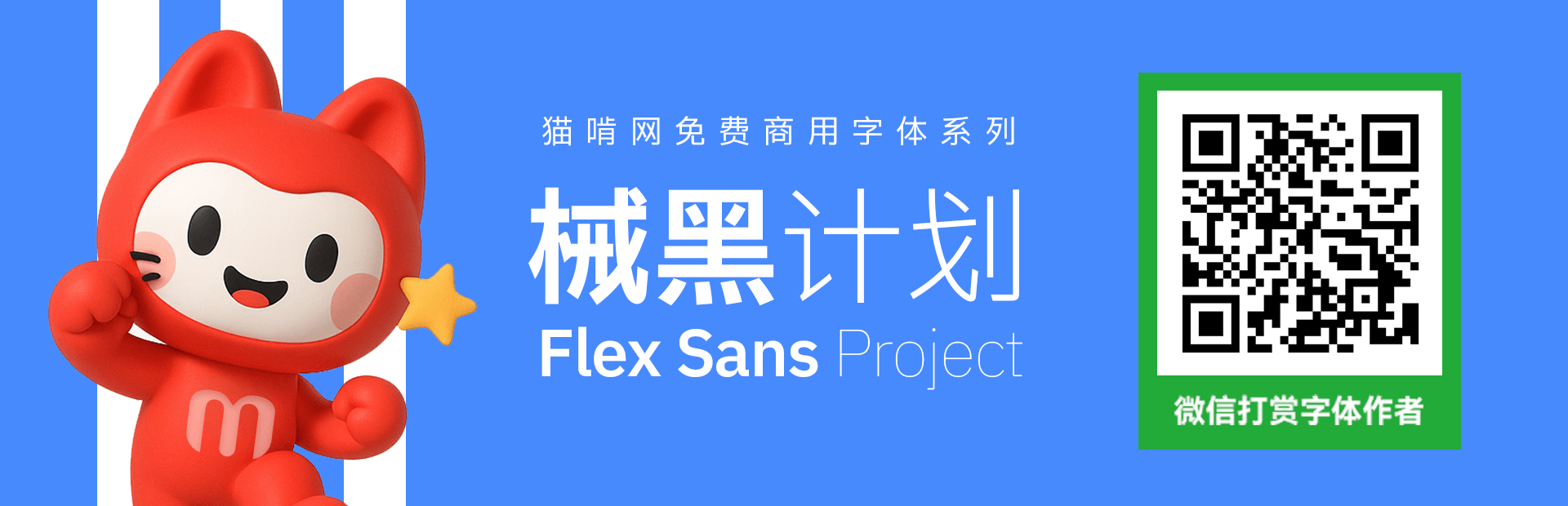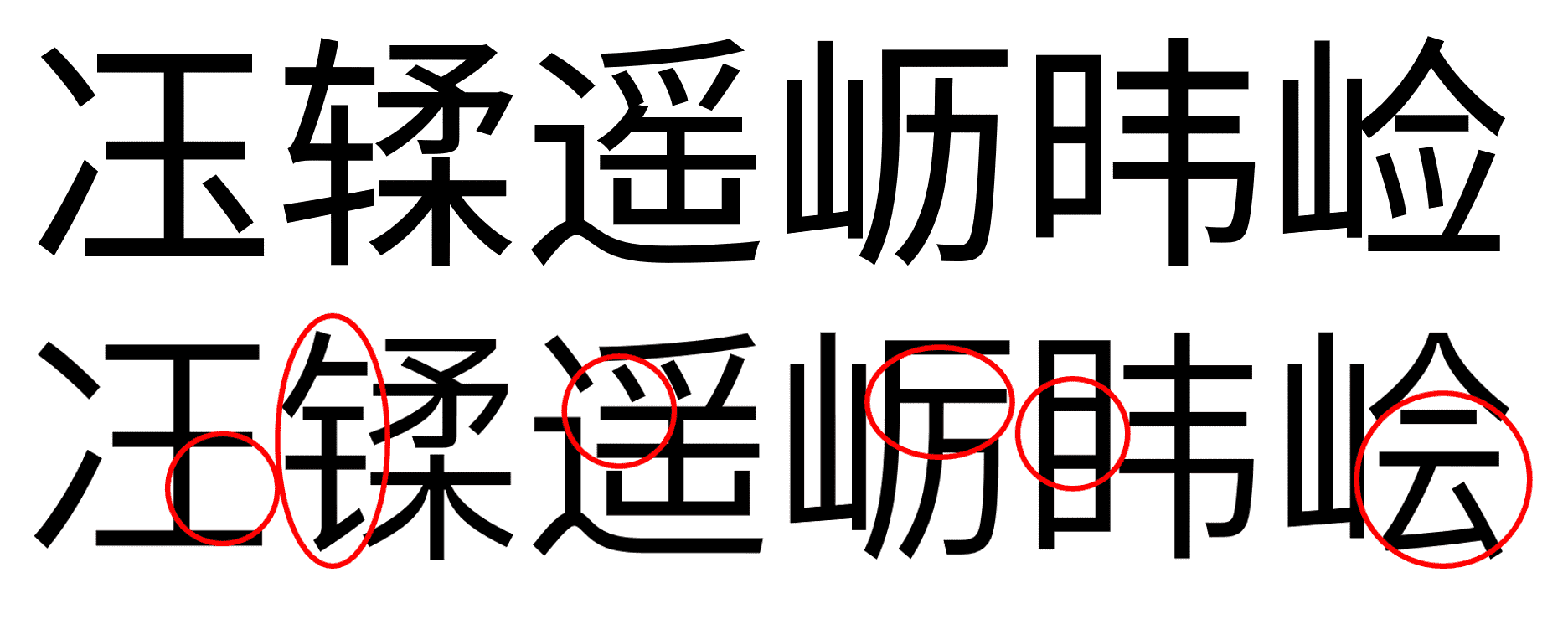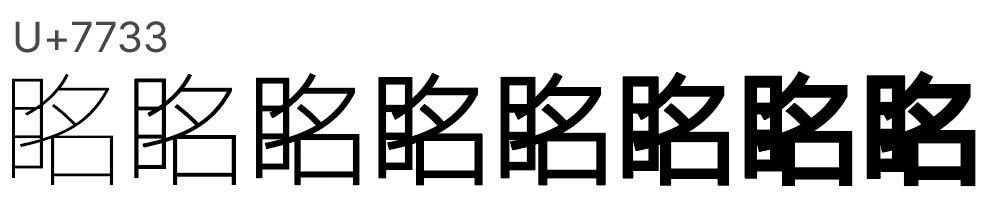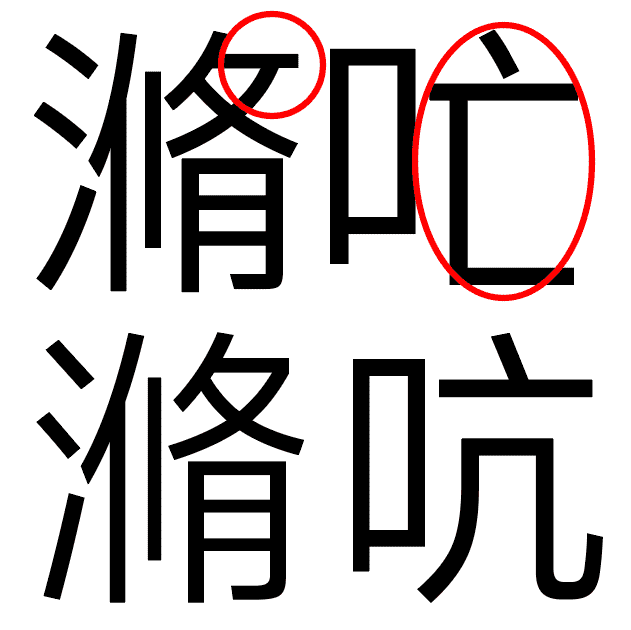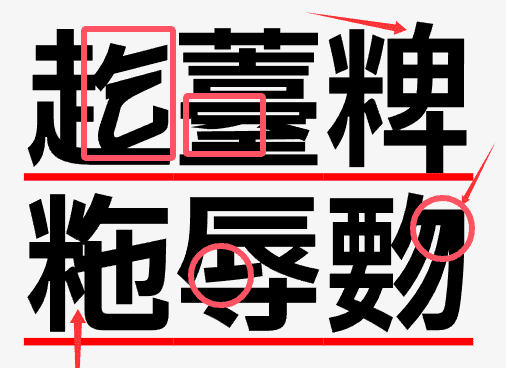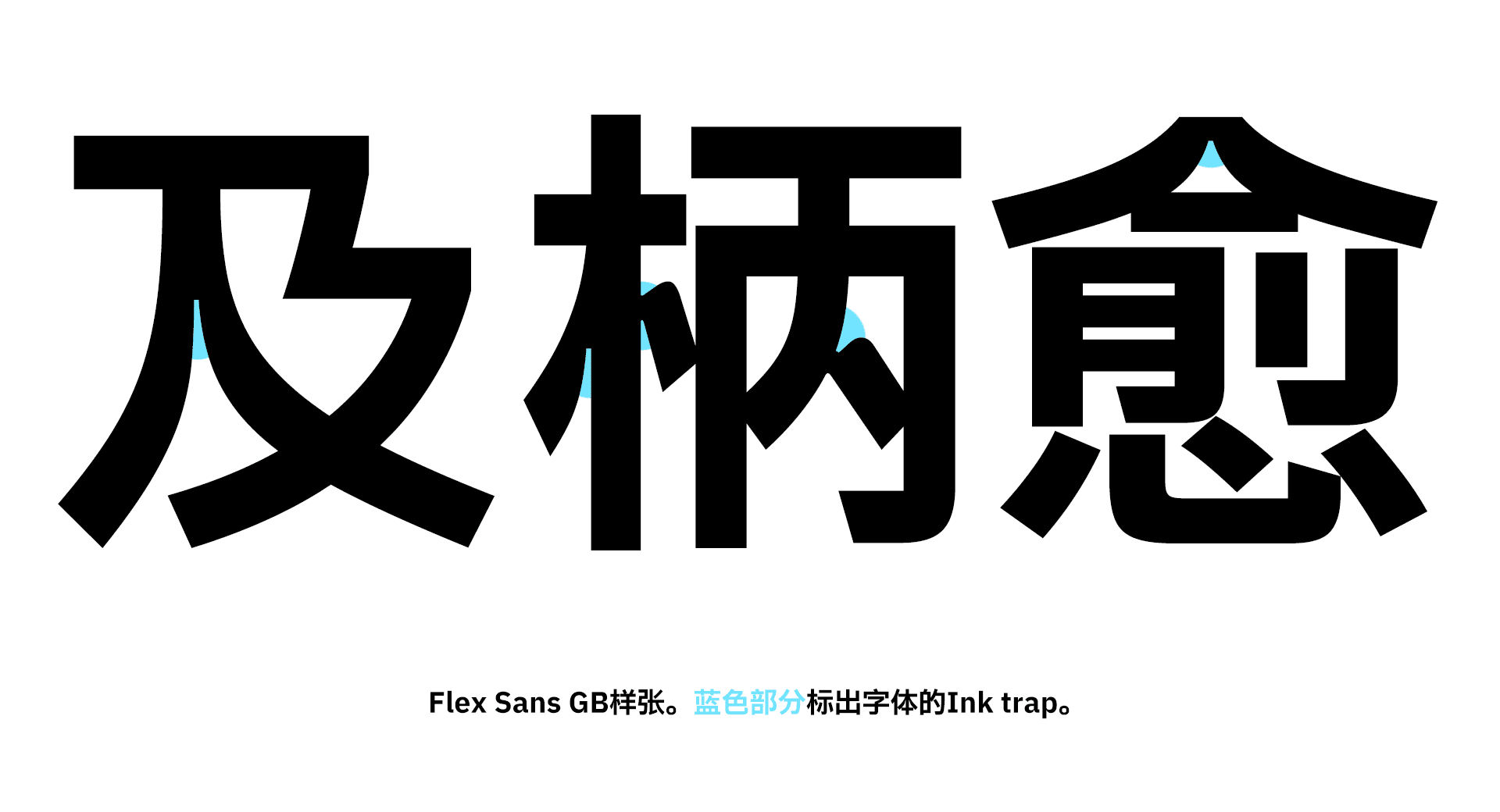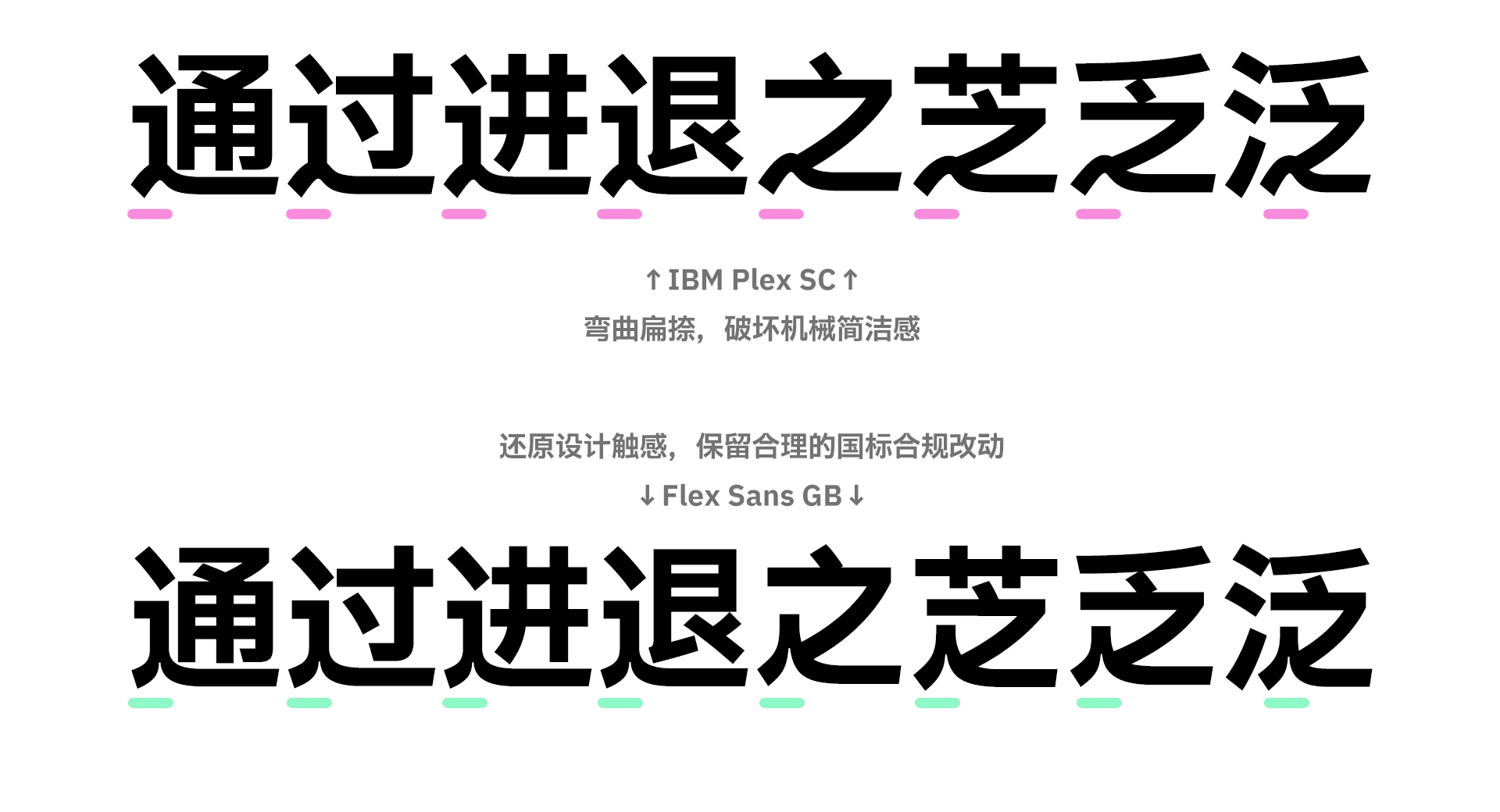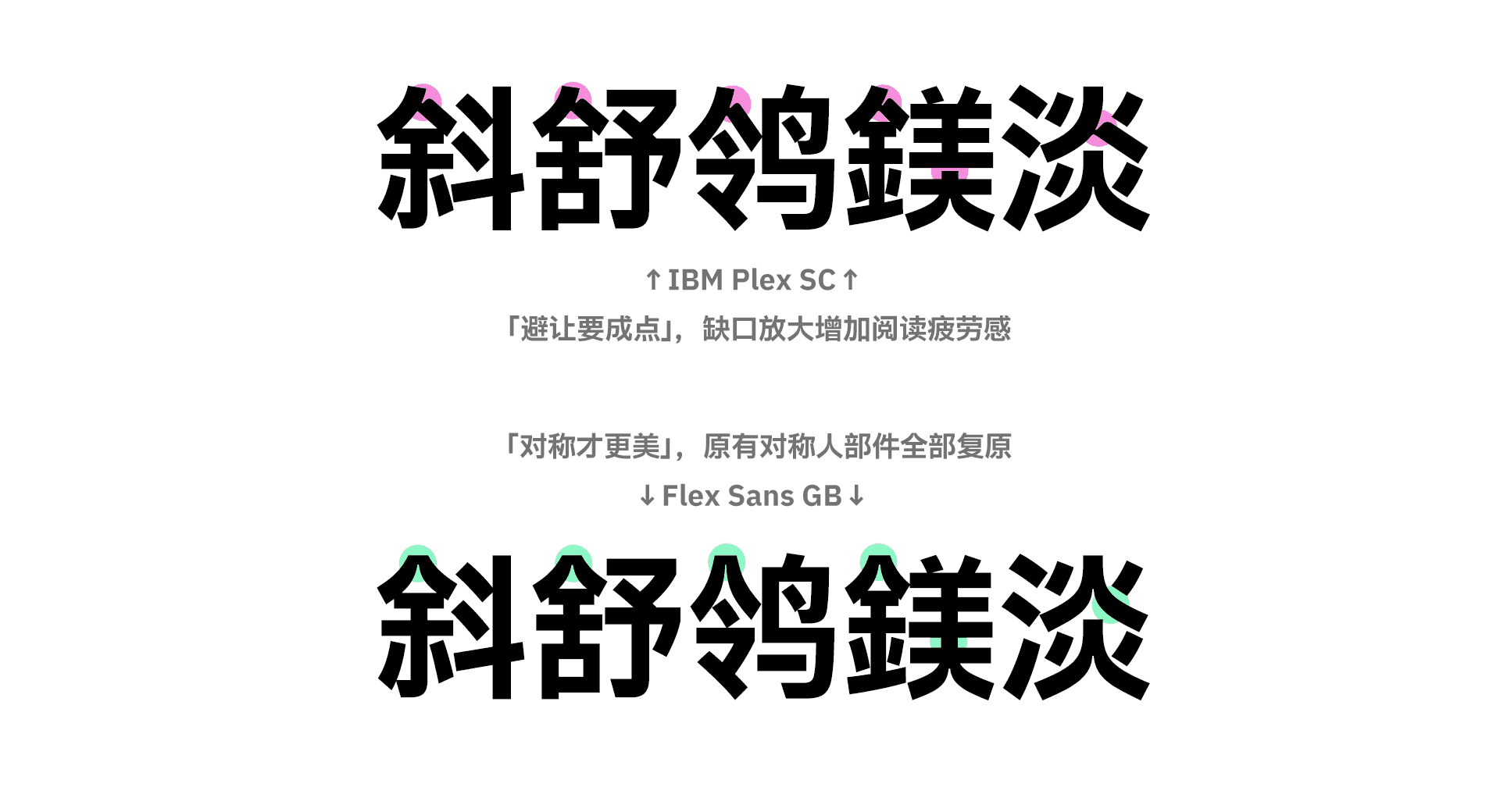
项目起因
IBM Plex,和一再放鸽子的IBM Plex CJK
IBM Plex是IBM公司于2017年发布的开源字体项目,在当时便预告说「会制作相应的CJK(中日韩)字体,预期在2018年中发布」,吊足胃口。可延期又延期,直到2021年7月,日文版才总算发布。其中汉字部分的设计上延续西文部分独特的ink trap表现,轮廓融合机械与人文,不失简约感,令人十分期待扩充汉字字数后的繁体和简体版。在用户的期待、敦促和不安中,2024年8月末我们迎来了其繁体版的发布,也可圈可点。一切似乎很顺利。
谁能想到IBM Plex Sans SC这么糟
可好景不长,后续发布的IBM Plex黑体简体版(下文称IBM Plex Sans SC,SC即「简体版」)令人大跌眼镜,不仅出于所谓「符合国标规范」的理由,将大量合理设计全部推翻,改为突兀而不合群的设计,令人费解,甚至出现了大量明显错字、轮廓错误变形等,尽显赶工丑态。大量遗漏未修改的断笔竖点更是自打「符合国标」的嘴巴。
Plex SC 部件比例错误
Plex SC 更多错字错形
Plex SC更多形体问题
Flex Sans GB的形成
直到2025年4月,IBM才匆匆发布Plex的字体源代码,我们也总算有机会对IBM Plex Sans SC的诸多问题拨乱反正,并得以借此制作汉字部分的可变字体版本。
项目创立时,我们先从中拿出简体中文实际会使用到的文字进行修改,并逐步确立了「尊重日文版和繁体版的原有设计风格,复原简体版不必要的修改」这一目标。历经几个月的修改工作,我们已初步将IBM Plex Sans SC中成部件的大量不必要修改还原成字体的原有风格,并修复了其中的一部分错形,部分零碎的字形也已恢复到繁体版和日文版原本的设计。时机成熟,我们决定发布成果,将这一恢复原本设计但也符合国标、拥有可变版本的字体命名为「Flex Sans GB」。
项目概览
人文机械巧结合
「按下键帽,金属臂带动字模,凸出的字形透过墨水晕印纸上。」这便是这套字体的灵感来源,IBM最初的产品之一,IBM Selectric打字机的感觉。Flex Sans GB继承IBM Plex CJK原版风格,从打字机中汲取灵感,在具有早期铅字的ink trap墨陷设计的同时,轮廓则尽可能简洁而倾向几何化,呈现出金属一般的利落感,兼具人文和机械特征,总体上在维持字体情绪为中性的同时,引入了与其他黑体与众不同的设计风格。
接下来,我们会介绍Flex Sans GB相对于IBM Plex Sans SC的改动,解释后者存在的问题,以及Flex Sans GB如何复原原始设计解决这些问题。
扁捺何须弯弯绕
对比扁捺,还原不必要修改(需更新)
IBM Plex Sans SC最为人诟病的修改,其中一个便是将大量的扁捺笔画改动成带有手写笔画特征的弯曲扁捺设计,破坏了原本设计简洁不失人文的特征,集中在辶、之两个部件上。我们在Flex Sans GB中将这些扁捺全部复原,并在兼顾国标合规的基础上,保留了斜点设计。
实际上,Flex Sans GB,或者说Plex原本的扁捺造型在国内字体大厂设计很多字体(尤其是定位偏艺术类,但风格也较为规整,一定程度上符合正文印象的字体,例如方正正黑)中都有类似的构造,完全不是一副「必须向上弯曲」的模样。IBM Plex Sans SC此番改动只是白费力气,吃力不讨好。
避让不是免死符
对比人部件,还原不必要修改
而另一个便是将居上的人部件(包括炎)靠右的笔画全部改成点的设计,大量制造新的视觉缺口。实际上,这种点的设计确实是原有Plex中所存在的(如「奇」字等)。但这样不惜大量压低重心制造阅读疲劳,却只是为了所谓的「避让」合规,就把所有合理的部件设计全部处理成令人乍舌的模样,绝对不是「简体版」应有的模样。同样,上文提到的方正正黑也完全存在对称的人部件设计,人部件的类对称设计根本不是应该为了所谓「避让」而必须修改的东西。
零散改动无用功
一部分零散改动,「圖」字为修复Plex SC未符合国标的问题
此外,团队中的成员结合已有的结论和自己的观察,也多多少少指出了IBM Plex Sans SC所做的其他不必要改动,多到此处不便一一列举。我们承认其中部分修改或许更符合部分简体用户的需求,但总的来说IBM Plex Sans SC的这些修改不尽人意,绝大多数改动相比繁体版和日文版只算得上「劣化」。
「面」「用」的不必要更动
再如「面」「用」等字,IBM Plex Sans SC对此的改动不知所云,细看则是单纯破坏中宫和谐。Flex Sans GB也已一一将这些不必要修改尽数还原。具体改动详见项目记录(如隹被包围时去脚、反跛脚处理等),远多于图中展示的这些。若还有漏网之鱼,敬请指出。
一些遗憾,一些实验
由于时间略有仓促,Flex Sans GB并不能包含原本项目包含的所有汉字,尽管我们采用了一个相对很大的针对简体实际需求的字表,但用户可能难免会用到一些本字体没有包含的字。
此外,IBM Plex Sans SC的部分简化部件设计我们未有时间逐个微调(尤其是简化字的讠部件,很多字,比如「让」,左右分家)。这部分的修改需要细细调整,比上述更改会更复杂,因而本次发布时未有调整。
有关「断笔」「竖点」等设计特征,我们计划于稍后新建项目,将上述所说需要从长计议的修改一并纳入。竖点在国内字体大厂(主要偏粗体)的艺术字设计中也十分常见,理论上IBM Plex Sans SC的有关设计也算作「不必要修改」,但考虑到Flex Sans GB项目是包含从细到粗体的可变字体项目,在当前阶段实现竖点无法保证细体状态下的美观,因而尚未付诸实践。至于不断笔,根据方正字库对筑紫系列修改时的阐释,我们也暂且保留Plex Sans SC的原样,将断笔留给新项目。
一些实验替代字形(下),上为默认启用的字形
在团队修改字形的过程中,我们提出过一些实验性的改动方案,制造了一些Plex原本没有但大致符合Plex风格的字形。这部分实验字形最终也包含在字体文件中,但没有默认启用,有需求的用户可以酌情调出使用。
说了这么多,到底什么是「地区审美」和「不必要修改」
目前为止的两套开源泛CJK字体项目,「思源」家族和「IBM Plex」家族同时发生了简体版大量的劣化修改问题。Flex Sans GB项目的出现有意打破部分人士以「地区审美」之名对此类跨语言开发字体的武断指导和对所谓「规范」的过度遵循,试图用实际作品阐述「什么才是真的合规改动」,「哪些只是一厢情愿的镣铐」。那么,所谓的「地区审美」究竟是什么呢?
实际上,字体开发中,跨语言开发是个重要议题。在东亚字体中,主要表现为「泛CJK字体」的制作,涵盖中文、日文等多种语言。初始设计字体(比如此处的IBM Plex)往往为日文字体,这就涉及了所谓「地区审美」概念及其带来的许多「不必要修改」。
当你看他人提笔写字的时候,你可能会注意到,每个人习惯的字的结构是不一样的。我们根据模仿的书法家、书写工具、个人风格等,把字分成了很多流派。每个国家或地区之间用字习惯不同,因此崇尚的流派也有所不同,形成了风格迥异的「地区审美」。实际上,「地区审美」这个词汇在电脑字体设计领域的来源,是部分设计师对于中国和日本字体设计不同风格取向的思考和总结。
但上面介绍的是书写领域,而在印刷领域,或者说电脑字体设计领域,情况可能会有一点点不同。
书写时,我们没有边界的束缚,因此操纵着线条的一维流动,在二维的平面上具有很多种可能性。而在电脑屏幕上,不论什么语言,从一开始每一个字都是在一个规定的小框框内,被当作二维图形制作出来的。设计师需要先让所有笔画一起分配掉整个框框,再让笔画和笔画之间分割的空间均匀舒适,还要让笔画的粗细在其空间内协调自然,最终让任意字组成文本时紧密流畅。
现在各位回想一下,前文所谓「流派」,说到底其实是笔画风格(笔形)的不同和空间分配(字形)的不同的组合。而在电脑里进行一套字体的设计时,这些参数已经被早早定下来,每一个字都必须严格遵循,也不允许有跳脱和独立。因此不论哪个字在书写时的各流派的审美习惯有多么不同,当它被放在同一款字体中经过规范制作后,其结果一定是大同小异的。但是,这并不意味着所有的电脑字体只能有同一个参数。当我们改变这些参数,也就是不同笔形和字形的排列组合,缤纷多彩的字体也就被设计出来了。
回到「地区审美」的问题上,根据上述逻辑,我们现在知道它实际上是不同地区人民习惯的字形参数的不同。也就是说,同一款字体相同的参数适配不同的「地区审美」其实是个伪命题。但是不同参数下的「地区审美」差异又是客观存在的。好在即使固定了各种参数,在字体制作过程中依然有容错性,人的眼睛会自己忽略掉这些不和谐。这就给了同一套字体挑出地区审美差异很大的字进行参数修改来迎合地区审美的可能性,这也是现在很多厂商在进行日文字体中文化时的做法。但是,这终究是修改了参数,必然会在同一套字体内部带来不和谐的观感。从另一个角度来说,既然人眼会自己忽略掉这些不和谐,那么这种地区审美的适配又是否必要呢?
结合例子一起说明
很多跨语言字体,如思源黑体,在简体中文版中为了迁就「地区审美」,进行了许多在构形(汉字本身写法)上改动前后无区别的修改。如「之」底下橫捺是否弯曲、「心」的三点的摆放位置、「名」是否偏头等。
事实上大部分「地区审美」的来源其实并不是对某个字的审美不同,而是成套的字体之间审美的不同。比如,鸟海修的「柊野」系列(即上文提到的冬青黑体简体中文的原型),虽然完全是根据日本人对汉字的理解制作,但其字形参数定下来刚好和中国人对汉字的审美很接近,所以中国人看着觉得很舒服。再比如,大部分中国人看习惯了华文黑体或者方正兰亭黑,看同样是鸟海修设计的日文字体天花板「遊」系列时,就会感到不舒服。所以,这些其实是设计体系之间的差异,其影响范围波及到每一个汉字。仅靠修改明显差异的字形,甚至是做一些几乎没有差别的修改,来实现「地区审美」适配,不仅是杯水车薪,还可能破坏风格统一性。上文提到的「思源」系列就是极具代表性的例子。
对于一些字体来说,设计师精心赋予字体的独特笔画特征,例如某个部首微妙的转折角度,笔画间优雅的断开处理,或是流畅极致的曲线,仅仅因为它们与当地主流商业字体中常见的处理方式略有不同,便被武断地抹平、同化。这种修改,并非基于对错,而是源于一种对「标准模样」的僵化理解,本质上是一种审美霸权,它无视了字体设计本身应有的多样性和艺术生命力。